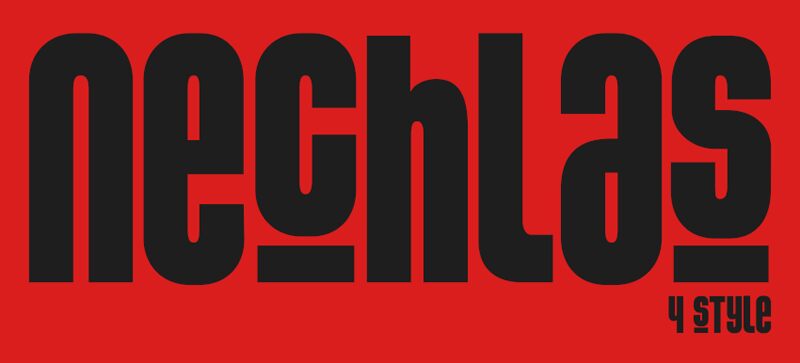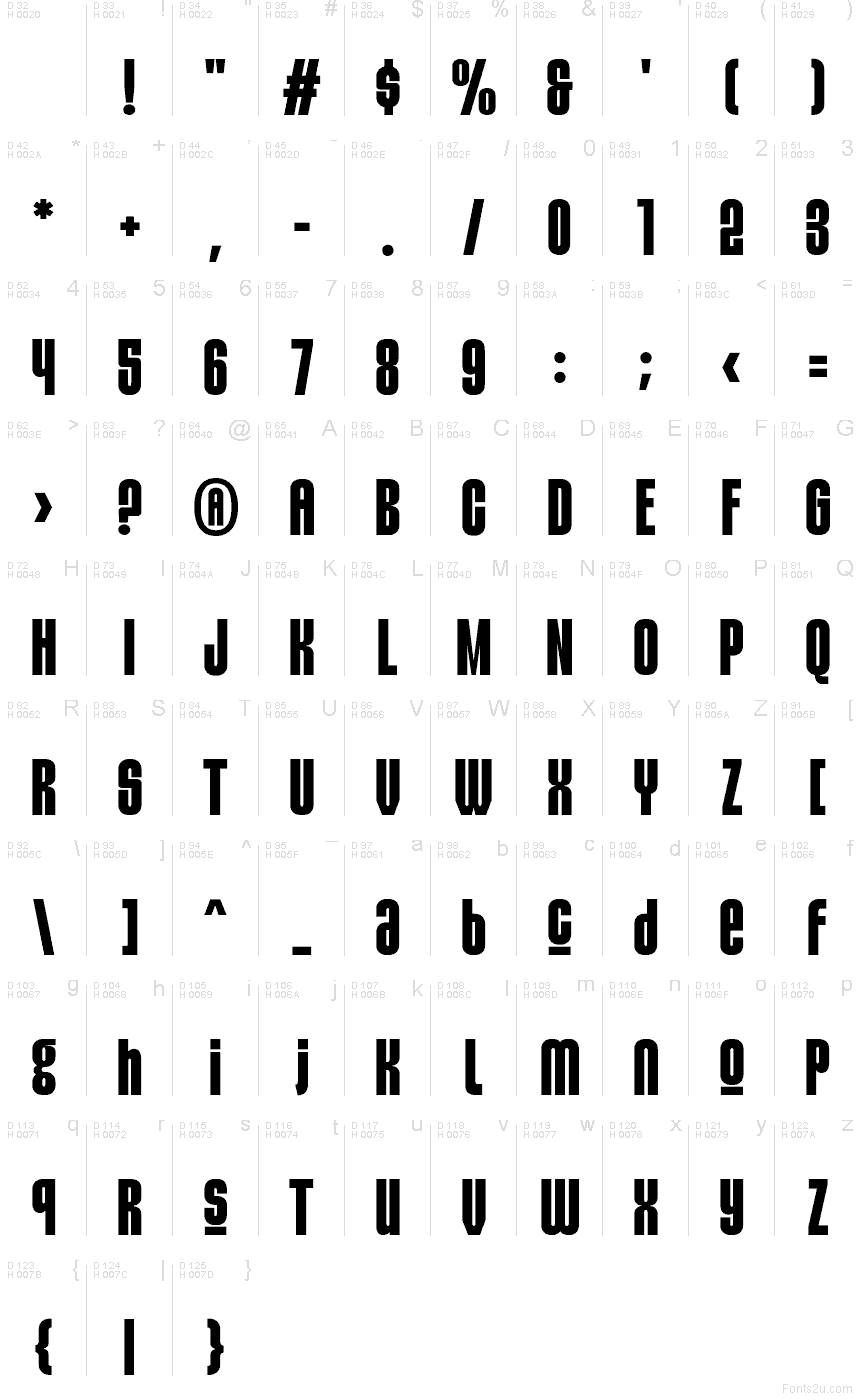
Nechlas od Glyphminds Studios to darmowy, ultra-wąski font typu display o wyrazistym, plakatowym charakterze. Litery są wysokie i precyzyjnie nakreślone, z silną pionową energią, ostrymi łukami i wąskimi prześwitami, co nadaje całości twardy, miejski rytm w nieco retro stylu nagłówkowym.
Idealnie sprawdzi się na plakatach muzycznych, w brandingu modowym, na okładkach magazynów, w tytułach oraz odważnych grafikach do mediów społecznościowych, gdzie krótkie słowa mogą w pełni wykorzystać jego skondensowany dramat. Jako darmowy font, świetnie nadaje się również do logotypów, monogramów i nazw na opakowaniach, które wymagają zwartej sylwetki, ponieważ litery niosą ogromny ładunek charakteru przy bardzo małej szerokości.